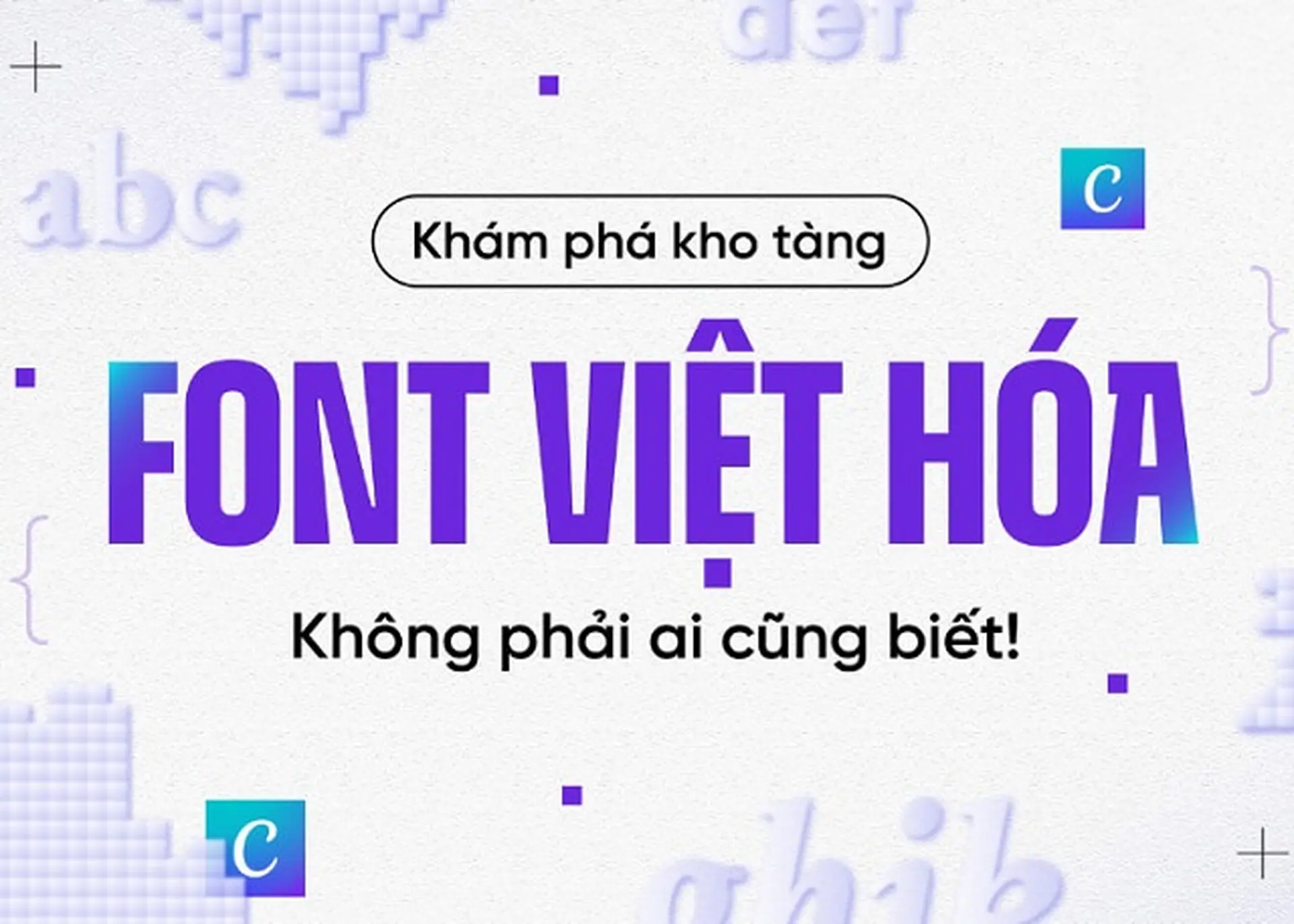
Danh sách font tiếng Việt Canva đẹp, dễ đọc và phù hợp cho mọi thiết kế sáng tạo
Việc sử dụng font việt hóa Canva không chỉ giúp thiết kế của bạn trở nên thẩm mỹ mà còn đảm bảo nội dung được hiển thị chính xác, chuyên nghiệp. Nhờ kho phông chữ Việt hóa đa dạng trên Canva, bạn có thể dễ dàng tìm thấy các kiểu chữ phù hợp với nhiều phong cách thiết kế khác nhau. Trong bài viết này, hãy cùng FPT Shop khám phá ngay danh sách những font tiếng Việt Canva đẹp, được yêu thích và sử dụng nhiều nhất hiện nay nhé!
Font Việt hóa và font chưa Việt hóa trên Canva có gì khác biệt?
Khi sử dụng Canva, việc lựa chọn giữa font tiếng Việt Canva đẹp và các font chưa Việt hóa là yếu tố quan trọng quyết định trải nghiệm người xem. Để giúp bạn có cái nhìn khái quát hơn về hai loại font thì FPT Shop đã tổng hợp bảng so sánh dưới đây:
Tiêu chí | Font tiếng Việt Canva | Font Canva chưa Việt hóa |
Hỗ trợ tiếng Việt | Hỗ trợ đầy đủ dấu và ký tự tiếng Việt, đảm bảo hiển thị chính xác trong mọi thiết kế. | Không hỗ trợ hoặc dễ gặp lỗi dấu, sai ký tự khi nhập tiếng Việt. |
Khả năng đọc hiểu | Rõ ràng, dễ nhìn, tối ưu cho văn bản tiếng Việt. | Tùy thuộc vào từng loại font, nhưng thường chưa tối ưu cho tiếng Việt. |
Tính thẩm mỹ | Tương thích với ngôn ngữ và văn hóa Việt Nam, dễ ứng dụng trong nhiều thiết kế. | Có tính thẩm mỹ cao nhưng chưa phù hợp khi dùng cho nội dung tiếng Việt. |
Số lượng font hiện có | Ít hơn so với font chưa được Việt hóa, tuy nhiên đang được bổ sung liên tục. | Số lượng nhiều và chiếm phần lớn trên Canva |
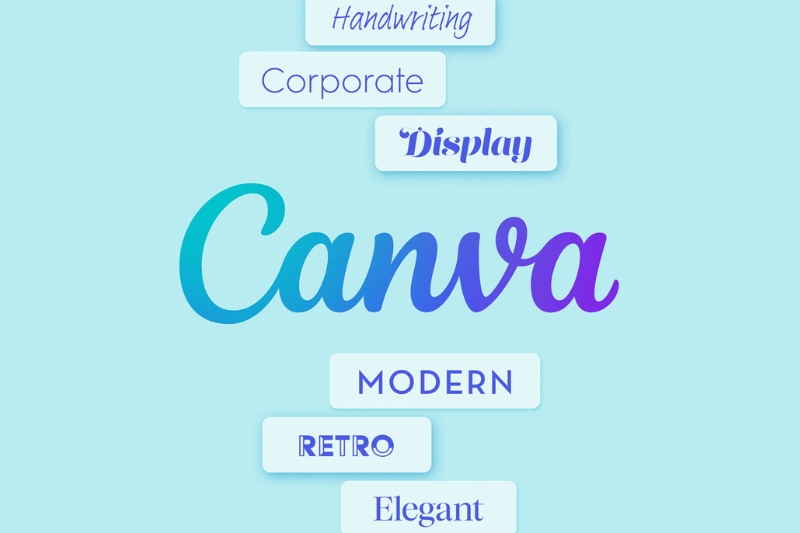
Tổng hợp các font tiếng Việt hóa Canva đẹp
Các font tiếng Việt Canva đẹp là lựa chọn hàng đầu của nhiều người khi thiết kế poster, banner hay bài đăng mạng xã hội. Không chỉ giúp văn bản hiển thị đúng chuẩn tiếng Việt, những font chữ này còn mang lại cảm giác tinh tế và hiện đại cho tổng thể thiết kế. Nhờ đó, sản phẩm của bạn vừa đảm bảo tính thẩm mỹ, vừa thể hiện được cá tính riêng biệt. Dưới đây là một số font Việt hóa trên Canva được ứng dụng nhiều nhất hiện nay:
STT | Tên font tiếng Việt Canva đẹp | Phong cách | Ứng dụng phổ biến |
1 | Đơn giản, hiện đại | Thiết kế tiêu đề, tên thương hiệu, nội dung chính | |
2 | Thanh lịch, cổ điển | Thiết kế ấn phẩm in ấn, tạp chí, thiệp mời | |
3 | Thanh thoát, dễ đọc | Website, trình chiếu, blog, content, bài viết dài | |
4 | Rõ ràng, đơn giản | Thiết kế infographic, tài liệu, bài thuyết trình | |
5 | Thư pháp uyển chuyển, lãng mạn | Typography nghệ thuật, thiết kế thiệp mời | |
6 | Nunito | Gần gũi, dễ tiếp cận | Nội dung về giáo dục, mạng xã hội |
7 | Be Vietnam | Năng động, hiện đại | Phù hợp với nhiều nội dung Tiếng Việt |
8 | Merriweather | Chuyên nghiệp, chuẩn mực | Báo chí, thuyết trình, văn bản dài |
9 | Pacifico | Phá cách, vui tươi | Các thiết kế sáng tạo, phá cách, thương hiệu cá nhân |
10 | Playfair Display | Cổ điển nhưng sang trọng | Thiết kế bìa sách, poster, logo, thương hiệu |
Cách tìm kiếm các font chữ Việt hóa trên Canva
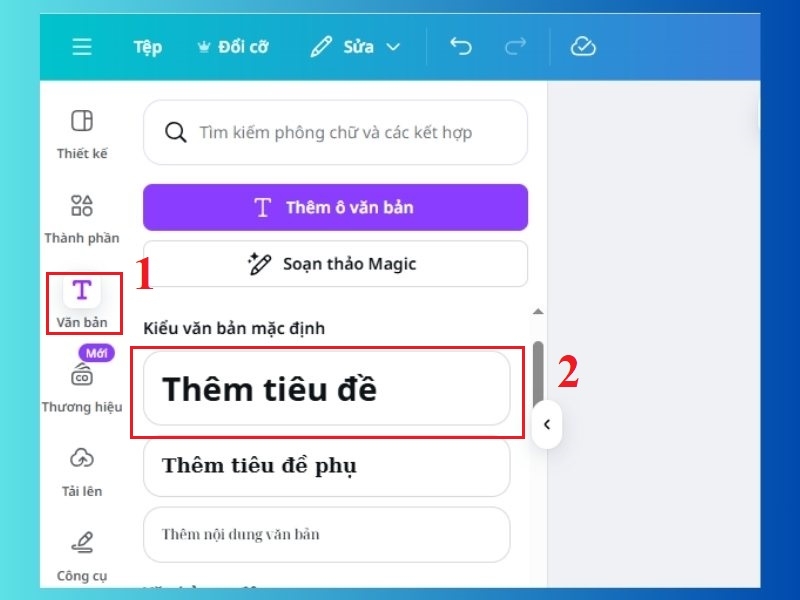
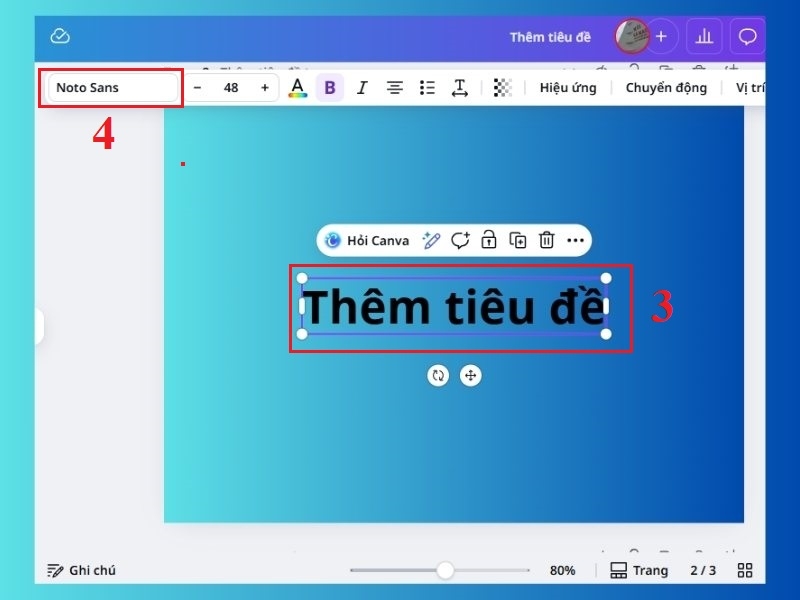
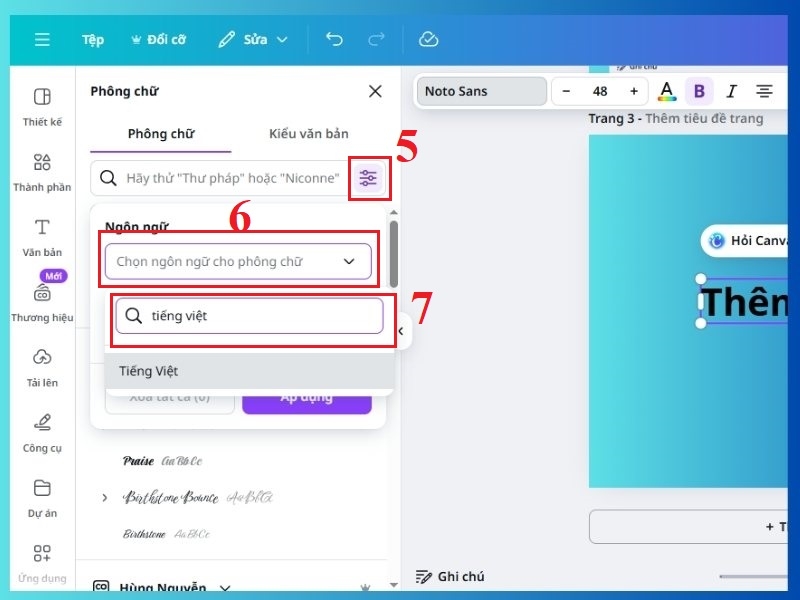
Bí kíp sử dụng font Việt hóa trên Canva hiệu quả
Việc chọn font tiếng Việt trên Canva sẽ giúp bạn tạo nên những thiết kế vừa đẹp mắt vừa chuyên nghiệp. Tuy nhiên, để tận dụng tối đa các font này, bạn cần nắm vững một số bí quyết sau:
Phối hợp font chữ hài hòa
Một thiết kế đẹp không chỉ đến từ hình ảnh mà còn từ cách bạn phối hợp hài hòa các font chữ. Chẳng hạn, bạn có thể chọn một font tiêu đề nổi bật như Montserrat hoặc Playfair Display với một font nội dung dễ đọc như Open Sans hay Roboto. Sự tương phản vừa đủ giữa nội dung và tiêu đề này sẽ tạo nên sự phân tầng rõ ràng mà chuyên nghiệp. Ngoài ra, bạn chỉ nên sử dụng từ 2–3 font trong một dự án để duy trì bố cục cân đối cho thiết kế.
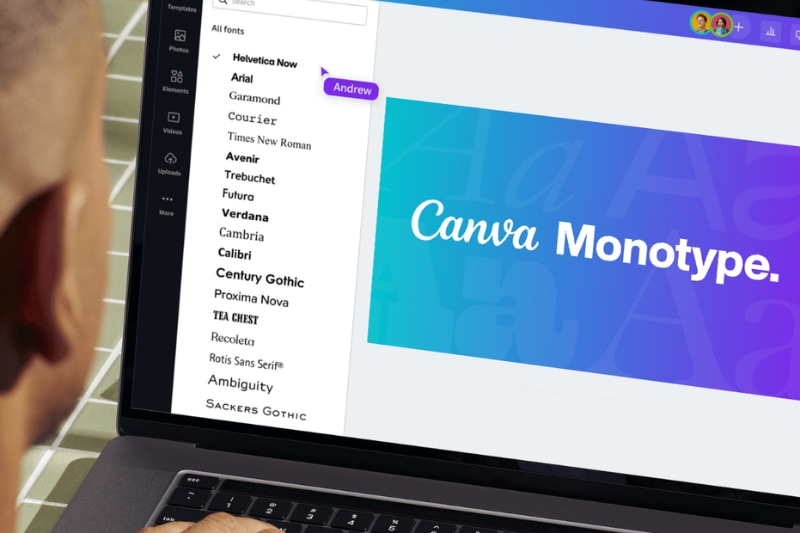
Lưu ý về bản quyền font chữ
Canva cung cấp hai nhóm font chính: font miễn phí dành cho tất cả người dùng và font trả phí chỉ khả dụng cho tài khoản Canva Pro. Nếu bạn sử dụng thiết kế cho mục đích thương mại, hãy đảm bảo font đó được cấp phép hợp lệ. Ngoài ra, khi tải phông chữ từ nguồn bên ngoài lên Canva, bạn cần tìm hiểu kỹ giấy phép sử dụng (license) để tránh các rủi ro pháp lý.
Tối ưu hiển thị font trên các thiết bị